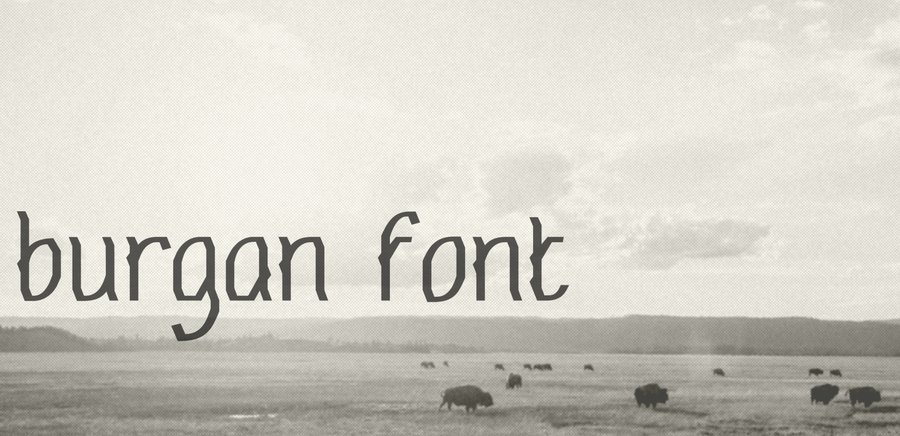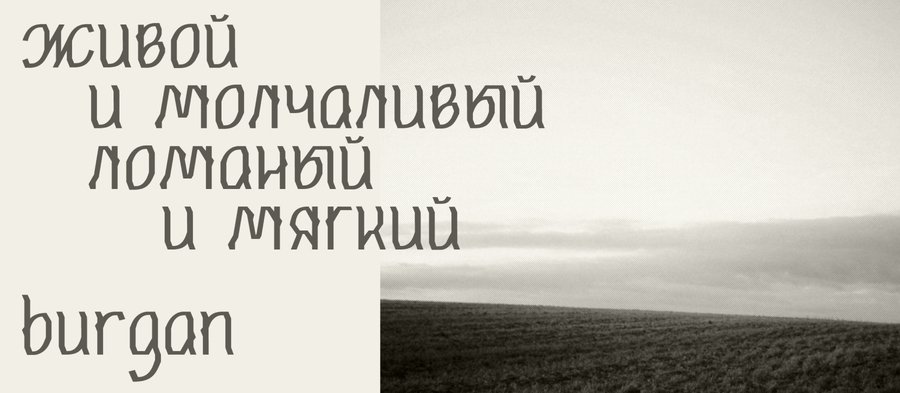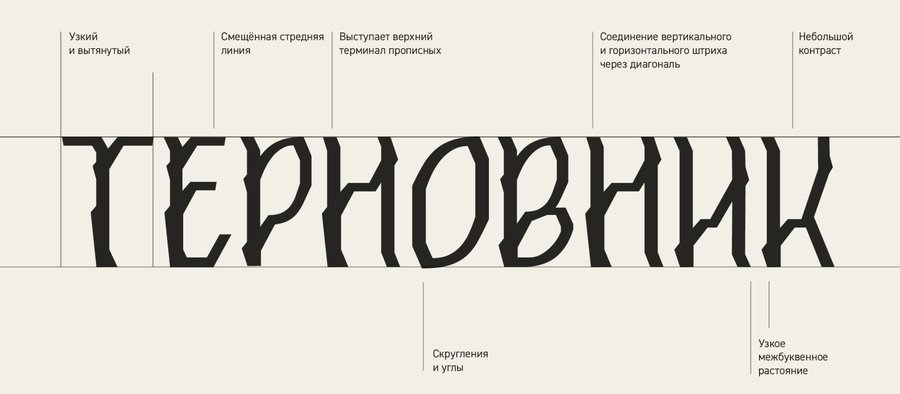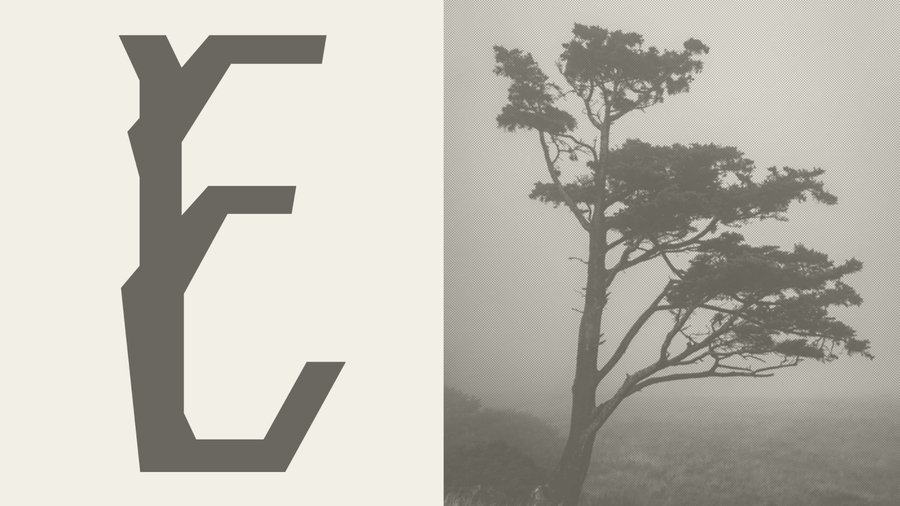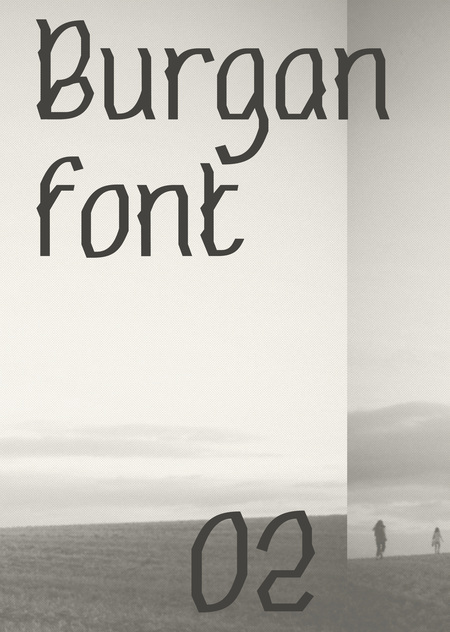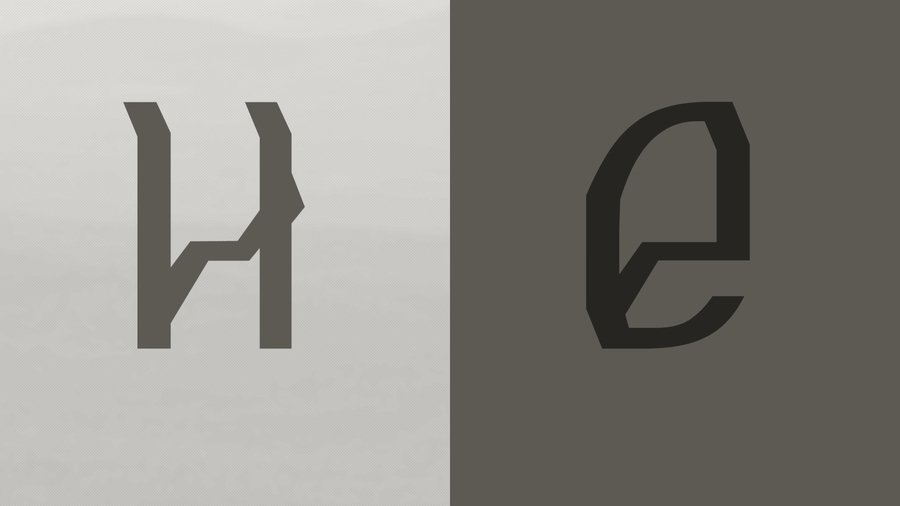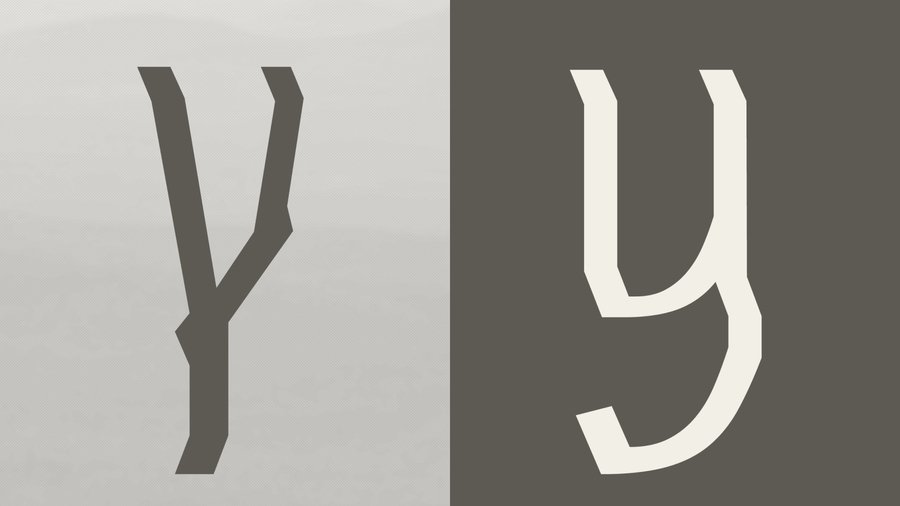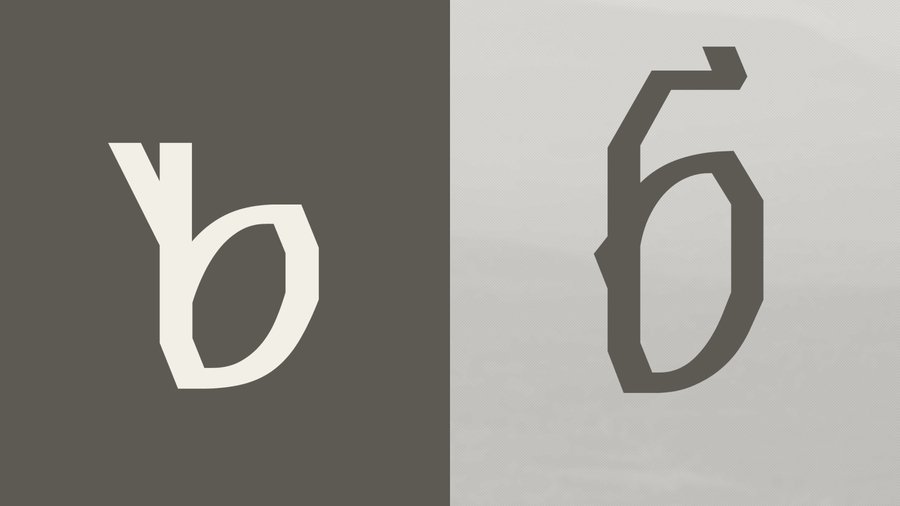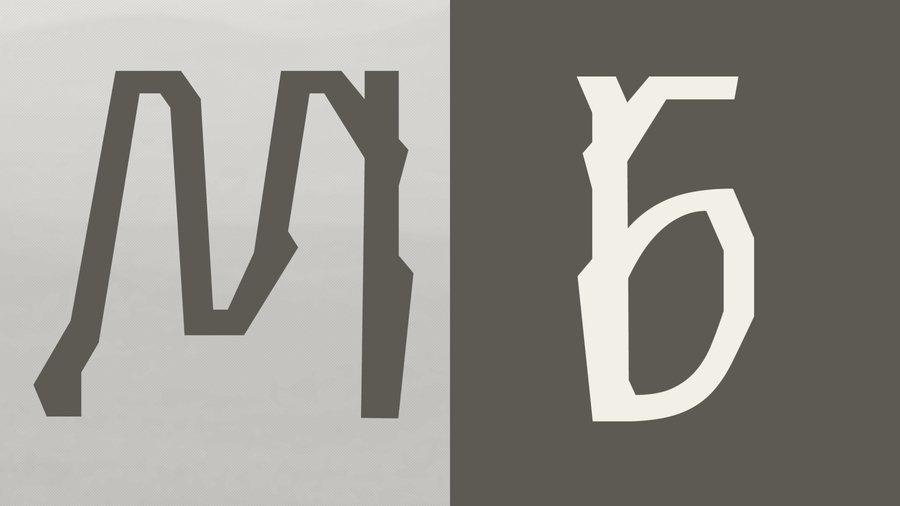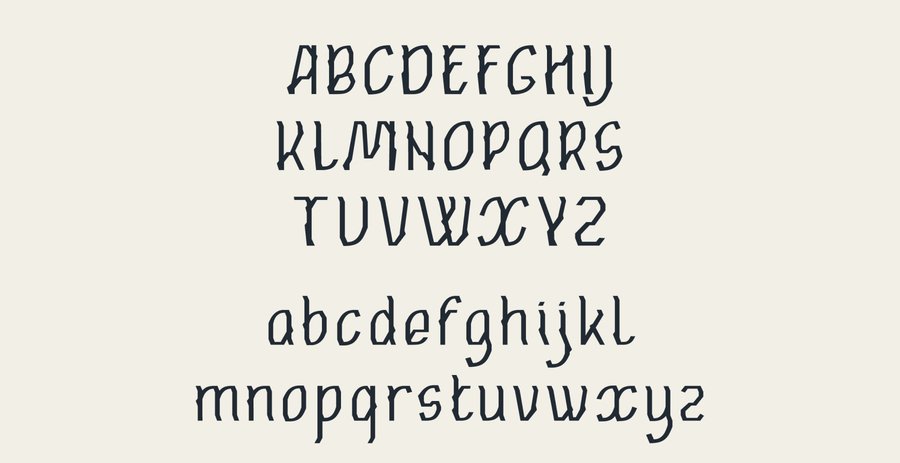
Шрифт Burgan вдохновлён суровой природой степей, ветвистыми деревьями и ветрами Бурятии.
В переводе с бурятского «бургааһан» означает кустарник — крепкое растение, одним из первых появляющееся после зимы. В нём сочетаются сила и стойкость с одной стороны, и витальность и естественность — с другой.